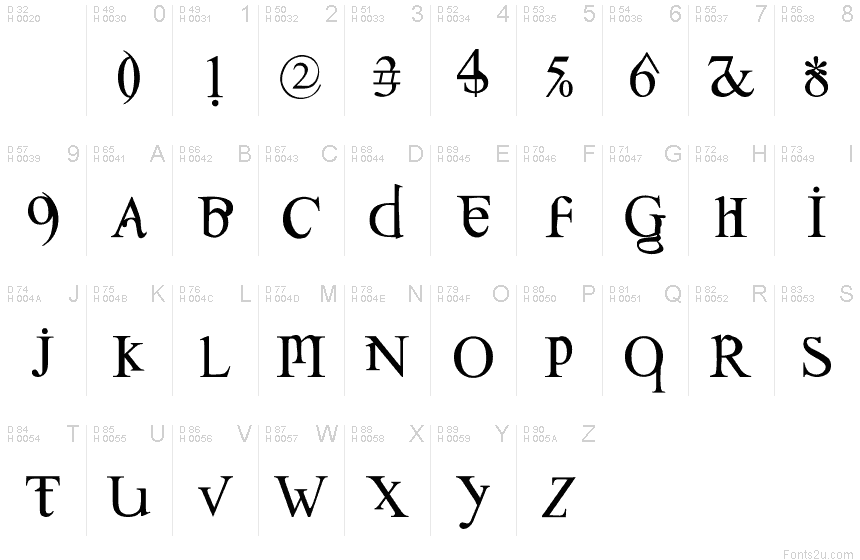
Confusebox autorstwa Johna Martza / Robotic Attack Fonts to darmowy, zniekształcony krój pisma, który wygląda jak klasyczna szeryfowa czcionka przepuszczona przez krzywe zwierciadła. Litery przechylają się, odwracają i wyginają na tyle, by wywołać niepokój – jak tekst, któremu trzeba przyjrzeć się dwa razy. Pociągnięcia pozostają wyraźne i nasycone, więc mimo chaosu słowa pozostają czytelne, zachowując buntowniczy i figlarny charakter.
Dzięki Confusebox zyskujesz wbudowane poczucie zagadki i dezorientacji, które świetnie sprawdza się w eksperymentalnych plakatach, glitchowych okładkach albumów, surrealistycznych tytułach książek, brandingu escape roomów, interfejsach gier mystery i awangardowych zinach. Ten darmowy font błyszczy w większych rozmiarach, gdzie jego pokręcony rytm jest najbardziej widoczny. Zestaw go z czystym, geometrycznym bezszeryfowym krojem w tekście głównym, aby zachować czytelność układu, podczas gdy nagłówki będą robić wrażenie.